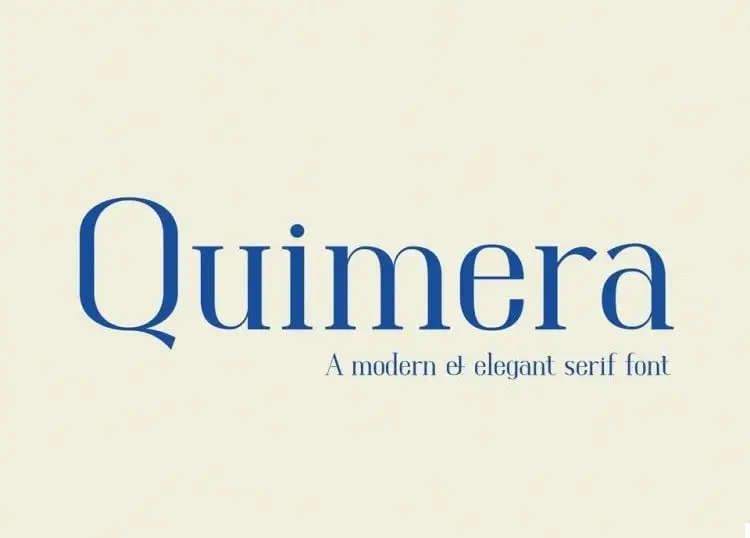
Quimera Serif Font – Fonte Grátis
Quimera Serif Font
A Quimera Serif Font é uma elegante escolha para designers que buscam trazer um toque nostálgico e vintage a suas criações digitais. Esta fonte serif apresenta um estilo grotesco e humanista, combinando elementos retro com ar de modernidade sofisticada. Suas características incluem letras maiúsculas e minúsculas básicas em latim e cirílico, oferecendo opções extensivas para projetos que exigem uma sensação de luxo e sofisticação. Composta por um conjunto sólido e bem equilibrado de letras, a Quimera Serifa Font é perfeita para quem busca criar designs únicos e extravagantes de maneira fácil e intuitiva. É uma escolha ideal tanto para aplicativos digitais quanto para criações gráficas que exigem um toque especial de sofisticação e charme dos anos 30 até os dias atuais.